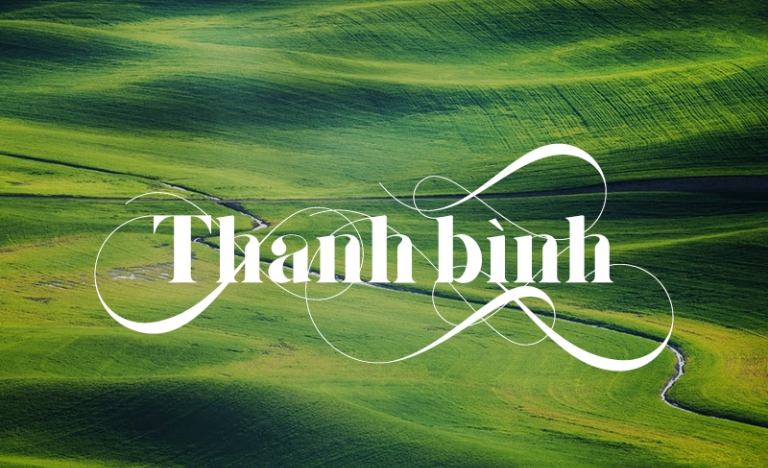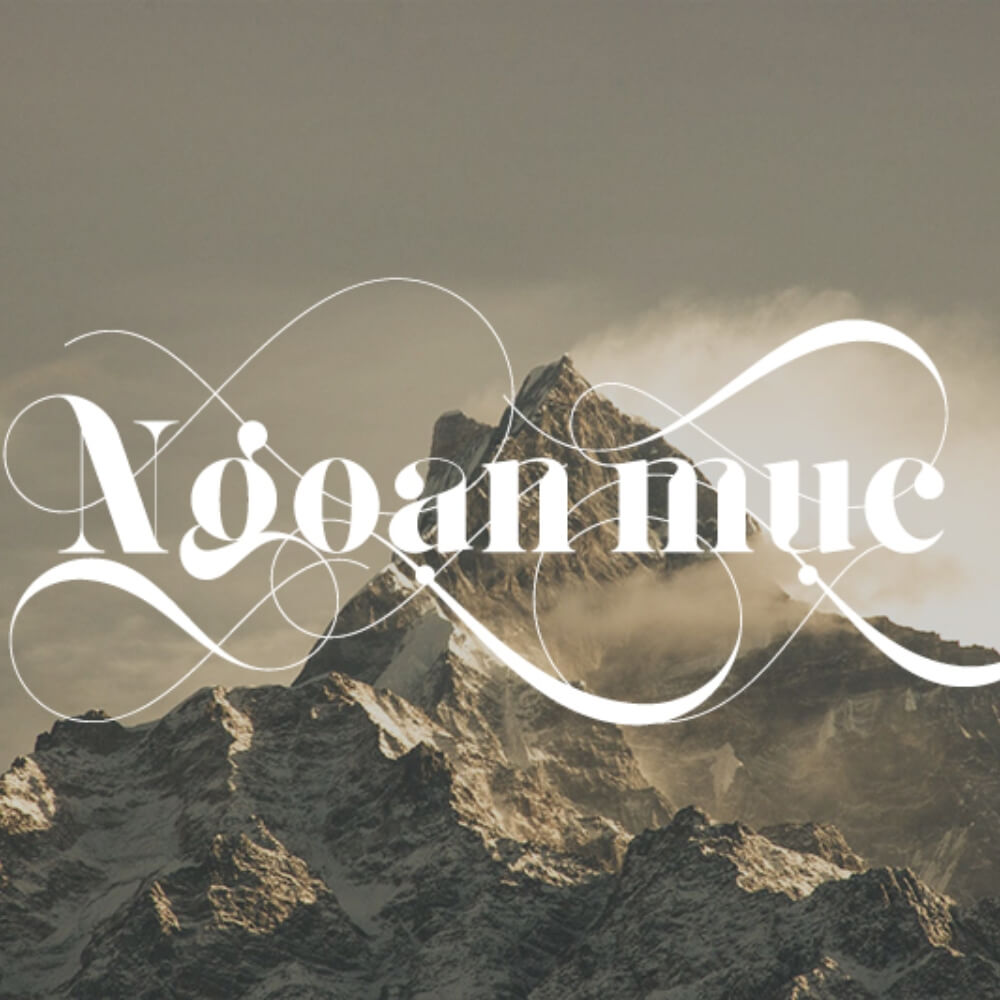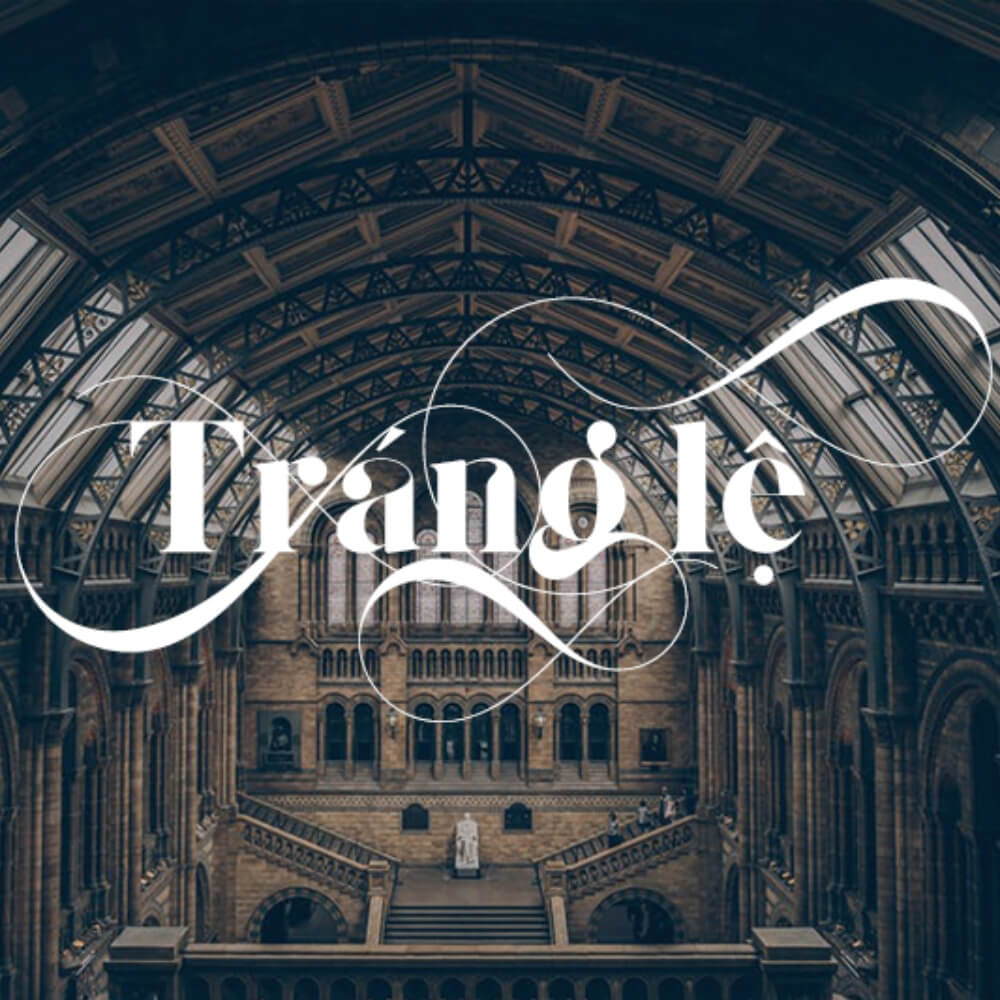
Trong lĩnh vực thiết kế đồ họa và kiến trúc, việc lựa chọn những bộ font chữ có tính định hình phong cách cao như Giaza sẽ giúp nâng tầm giá trị thẩm mỹ cho toàn bộ dự án. Font SVN Giaza Việt hóa là một đại diện tiêu biểu của dòng Modern Serif, nổi bật với sự tương phản mạnh mẽ giữa các nét thanh và nét đậm, mang lại vẻ ngoài quý phái và đầy tính nghệ thuật.
Sức hút từ ngôn ngữ thiết kế của font SVN Giaza Việt hóa
Phiên bản font Việt hóa SVN Giaza đã được đội ngũ SVN tinh chỉnh bộ dấu tiếng Việt tỉ mỉ, giúp các dấu thanh không làm ảnh hưởng đến cấu trúc mảnh mai đặc trưng của các nét thanh. Điều này giúp văn bản luôn duy trì được sự cân đối, thanh lịch trên mọi ấn phẩm thiết kế.
Bên cạnh yếu tố thẩm mỹ, Giaza còn sở hữu khả năng truyền tải thông điệp về sự chỉn chu và tư duy thẩm mỹ có gu. Khi được ứng dụng vào tiêu đề, font chữ này tạo ra nhịp điệu thị giác lôi cuốn, giúp thông tin trở nên nổi bật và dễ ghi nhớ hơn. Đây là giải pháp phù hợp cho những ai đang tìm kiếm sự giao thoa giữa nét đẹp cổ điển và tinh thần hiện đại để hoàn thiện các ý tưởng thiết kế và sản phẩm sáng tạo của mình.
| Phân loại phong cách | Modern Serif / Fashion / Elegance |
| Đặc tính hiển thị | Độ tương phản cao, nét thanh mảnh sắc sảo |
| Mục đích phù hợp | Tiêu đề, Branding, Poster, Hồ sơ dự án |
Gợi ý phối hợp: Để bản thiết kế đạt được hiệu quả thị giác ổn định, bạn nên phối hợp SVN Giaza cùng một font không chân tối giản cho phần nội dung chi tiết. Sự kết hợp này giúp phần tiêu đề của bạn trở nên nổi bật mà vẫn giữ được sự chỉn chu cho tổng thể bố cục.
03 Ứng dụng font Việt hóa SVN Giaza trong nhận diện công trình
Với diện mạo sang trọng và tính nghệ thuật rõ nét, bộ font này mang lại giá trị cao khi được ứng dụng vào thực tế quảng bá và trang trí các không gian hiện đại:
- Bảng nhận diện cho Homestay & Boutique Hotel: Những nét chữ Giaza rất ăn ý khi xuất hiện trên các biển hiệu bằng mica gương, inox hoặc khắc laser trên các vật liệu tự nhiên. Đối với các dự án nhà lắp ghép nghỉ dưỡng, font chữ này giúp nâng cao vị thế và tạo ấn tượng về sự chuyên nghiệp đối với du khách.
- Tiêu đề hồ sơ năng lực kiến trúc: Sử dụng font này cho các trang mục lớn trong hồ sơ dự án giúp thể hiện rõ gu thẩm mỹ và năng lực sáng tạo của đơn vị thiết kế, tạo niềm tin cho đối tác và khách hàng.
- Trang trí nội thất và số phòng nghệ thuật: Bạn có thể dùng font Giaza để làm các bảng tên phòng hoặc biển chỉ dẫn tại sảnh chờ văn phòng container nhằm tạo điểm nhấn đầy thanh lịch cho không gian sống và làm việc.
03 Lưu ý kỹ thuật khi trình bày bố cục với bộ font SVN Giaza
Để khai thác hiệu quả vẻ đẹp của dòng font Serif cao cấp này mà không làm rối mắt người đọc, người thiết kế nên lưu tâm một số kinh nghiệm sau:
- Kiểm soát kích thước hiển thị: Do có những nét thanh cực kỳ mỏng, Giaza phát huy hiệu quả thị giác tốt khi được trình bày ở kích thước trung bình đến lớn. Ở kích thước quá nhỏ, các nét thanh có thể bị mờ nhòe hoặc gây khó đọc.
- Cân nhắc độ phân giải in ấn: Khi in ấn các ấn phẩm khổ lớn như bảng hiệu hay poster, hãy đảm bảo tệp thiết kế đạt độ phân giải cao để giữ nguyên được sự sắc nét của các chân chữ và nét thanh mảnh.
- Lựa chọn nền màu tương phản: Font Giaza trông sang trọng hơn khi đặt trên các nền màu đơn sắc như đen, trắng, vàng đồng hoặc các tông màu trung tính đậm để tôn vinh sự tinh tế của từng ký tự.